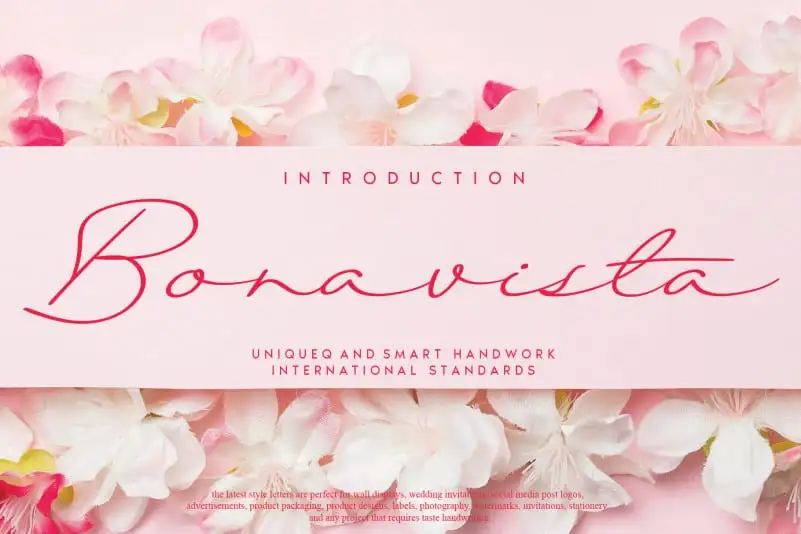
Bonavista Handwritten Font – Download Grátis
Aqui está uma descrição natural e envolvente para a página de download da fonte Bonavista Handwritten Font: Bonavista é um gênio entre as handwritings, sua personalidade expressiva e delicada, faz dela uma escolha perfeita para projetos que desejam dar vida às suas ideias em forma visual única. Este tipo de escrita é ideal para textos pessoais, anúncios, design gráfico e até mesmo artesanato, trazendo um toque único e autêntico a qualquer projeto. Composta por linhas sutis e traços elegantes, Bonavista oferece uma opção perfeita para quem busca expressar a sua essência de maneira única. Suas curvas fluidas e detalhes exatos são perfeitamente adaptados aos textos legíveis e encantadores que desejamos imprimir na nossa identidade visual. Escolha Bonavista para seu próximo projeto, e deixe-o impressionar seus leitores com uma escrita autêntica e memorável. A fonte é fruto do talento de um designer profissional, a andikastudio, que criou esta obra especial para adicionar profundidade e individualidade às suas criações. Experimente Bonavista hoje e deixe-nos ajudar você a destacar-se no mundo da design visual.